Ada banyak jenis font yang bisa digunakan pada logo coffee untuk mewakili karakter brand. Gaya font logo coffee seringkali tampil elegan, sederhana, dan minimalis. Style font logo coffee bisa menggunakan berbagai gaya seperti tipis, tebal, serif, hingga script sesuai kebutuhan.
Desain brand coffee sering menggunakan tipografi sederhana agar memudahkan nama brand terbaca. Sering juga brand coffee memodifikasi tipografi agar tampil unik dan bisa digunakan sebagai identitas brand coffee. Logo coffee modern biasanya akan dirancang untuk tampil bersih dan sederhana agar relevan.
STYLE DESAIN LOGO KOPI MODERN
Gaya desain logo coffee akan dirancang agar merepresentasikan identitas brand dengan baik dan jelas. Kesederhanaan menjadi kunci penting untuk membangun kepercayaan pada brand coffee. Biasanya logo kopi modern akan memiliki style desain logo seperti:
Style Logo Line Art
Logo line art banyak digunakan dalam desain logo coffee karena efektif menciptakan tampilan yang estetik dan minimalis. Style desain logo line art memiliki garis-garis bersih dan sederhana. Bentuk simbol dan tipografi menggunakan garis yang bersih sehingga menciptakan desain logo minimalis.
Ikon Biji Kopi dan Cangkir
Style logo kopi umumnya juga memiliki ikon logo yang mewakili identitas brand coffee agar mudah dikenali. Ikon yang cocok untuk digunakan pada logo coffee seperti biji kopi dan cangkir. Cangkir dan biji kopi cukup sering digunakan dan efektif merepresentasikan brand kopi dengan baik.
Warna Coklat dan Hitam
Sementara itu warna yang cocok untuk brand coffee juga harus minimalis seperti warna netral. Warna coklat dan kopi paling relevan mewakili bisnis coffee karena seperti warna produk kopi. Daripada warna lainnya, kedua warna ini cukup sering digunakan dan efektif merepresentasikan identitas brand coffee.
Font Elegan dan Klasik
Sementata brand coffee menggunakan style font yang sederhana, klasik, dan elegan untuk menciptakan logo coffee yang profesional. Gaya font elegan pada brand coffee sering memiliki garis tipis, halus, dan sudut lancip. Font logo coffee juga seringkali memiliki style font klasik seperti serif klasik agar mewakili identitas brand coffee premium.
4 STYLE FONT DALAM LOGO COFFEE
Tipografi dalam logo coffee tidak hanya berguna membuat nama brand mudah dibaca tetapi juga mewakili karakter brand. Logo coffee sering menggunakan gaya tipografi sederhana yang unik dan memiliki style minimalis. Berikut contoh beberapa style font yang berbeda-beda dalam logo coffee tersebut.
Logo Uma Kentara
Desain logo untuk bisnis kopi tersebut menggunakan style ikon dengan gaya line art sehingga menciptakan desain minimalis dan bersih. Ikon logo coffee tampak memiliki kombinasi cangkir, daun, garis, dan geometris lingkaran. Gaya ikon line art minimalis cocok dikombinasikan dengan font sans serif tinggi yang sederhana.
Gaya huruf tinggi atau condensed tersebut membuat logo coffee memiliki gaya modern dan mudah dibaca. Font sans serif yang tinggi membuat logo coffee memiliki kesan profesional dan handal. Kerning yang dibuat dalam tipografi logo membuat style font tinggi lebih mudah dibaca dan menciptakan logo yang bersih.
Logo Tu Mbale Kopi Bubuk
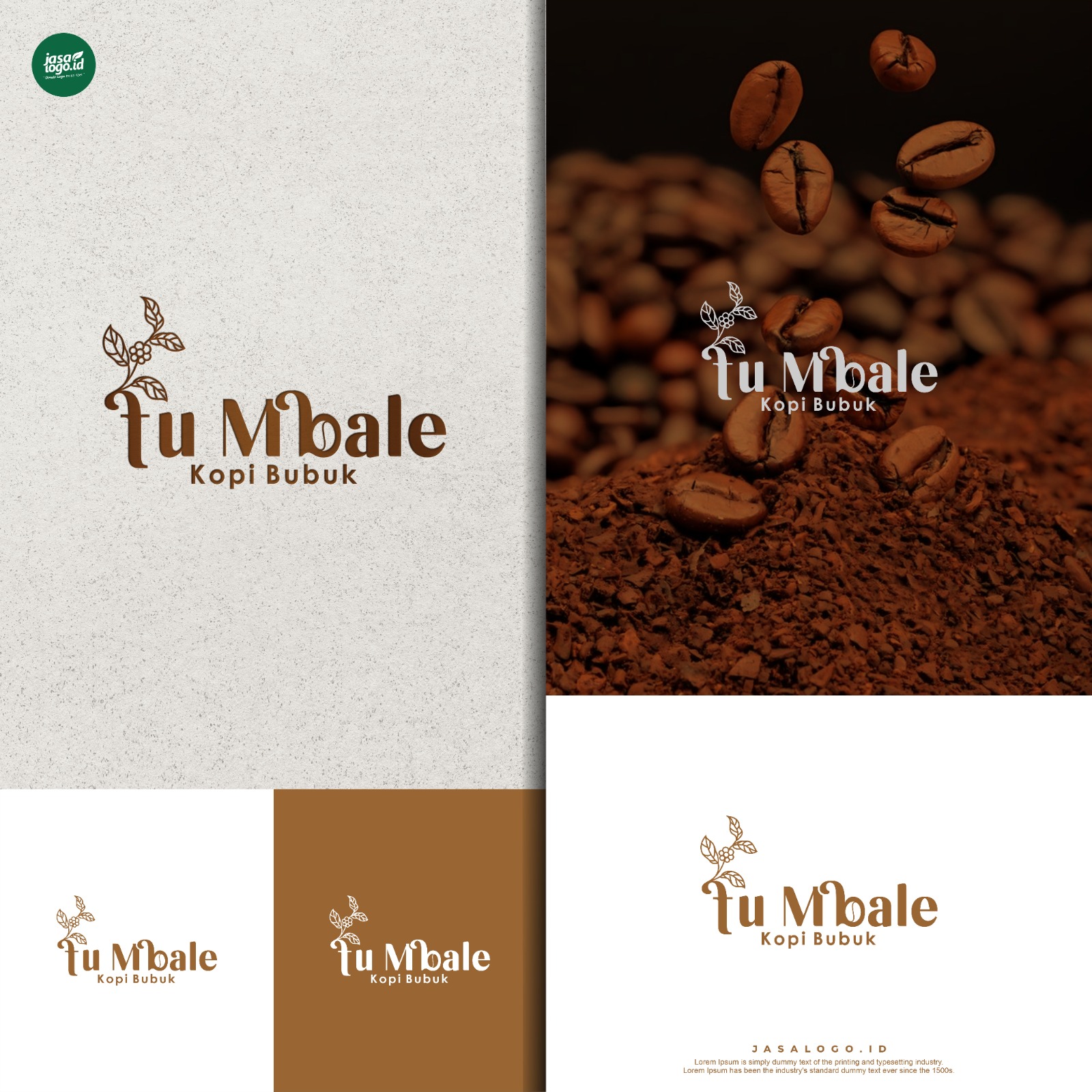
Desain logo coffee ini menggunakan gaya tipografi serif yang elegan sehingga menciptakan brand coffee yang elegan. Font serif elegan tersebut juga berguna memberi kesan brand coffee yang premium. Tipografi serif dalam logo tersebut memiliki gaya huruf sederhana, halus, dan memiliki sudut lancip.
Gaya tipografi pada logo coffee tersebut tidak hanya elegan tetapi juga tampil unik karena beberapa hurufnya memiliki ujung yang melengkung. Desain logo hanya memiliki tipografi dengan dekorasi daun yang sederhana. Kombinasi tipografi elegan dan simbol daun kecil menciptakan desain logo coffee yang elegan dan estetik.
Logo Warkop Logo
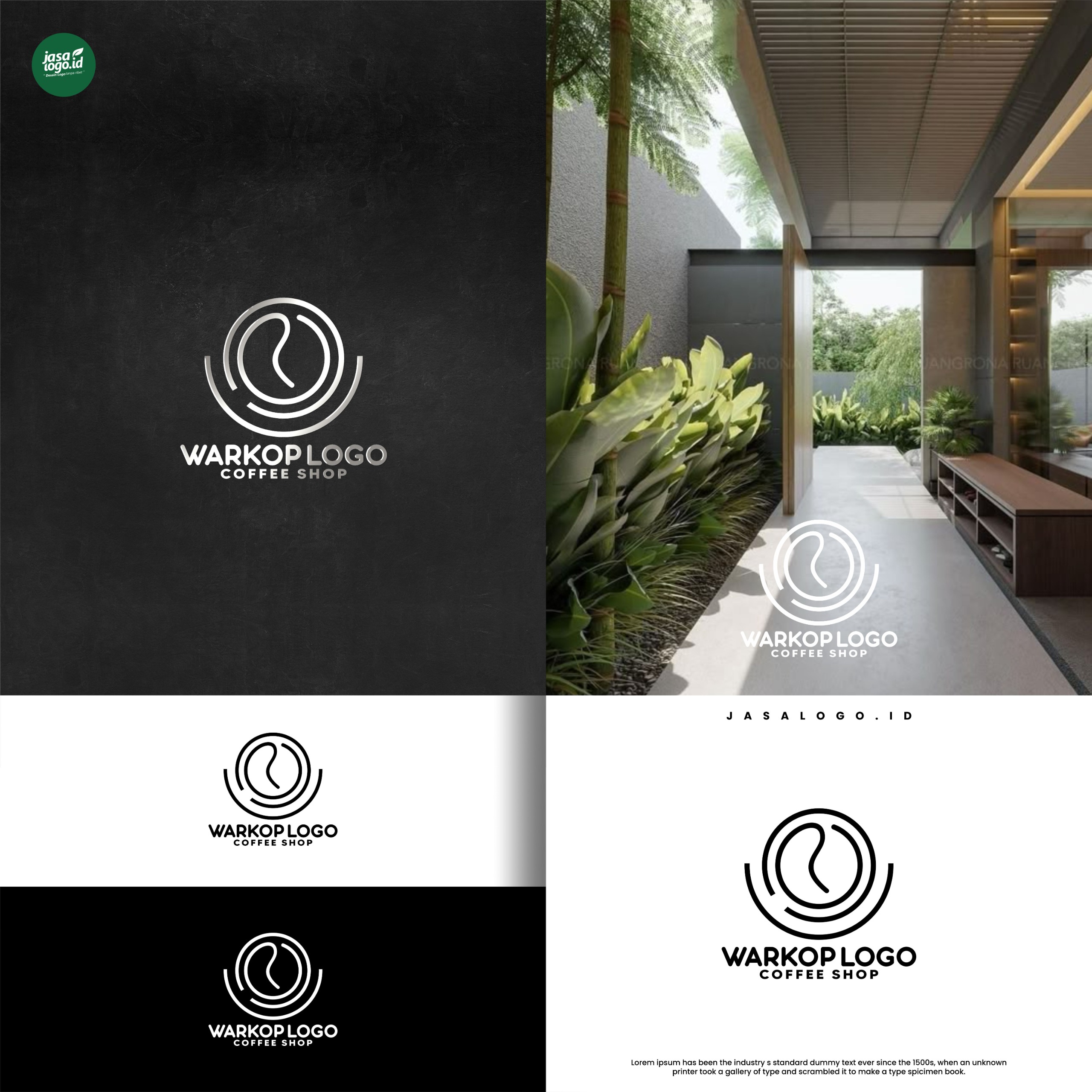
Style garis line art yang menciptakan bentuk lingkaran biji kopi tampil minimalis dan sederhana. Desain logo kopi line art ini menggunakan garis tipis yang elegan dan bersih. Style ikon geometris tersebut cocok dikombinasikan dengan gaya tipografi geometris yang sederhana.
Font sans serif yang digunakan memiliki gaya huruf geometris yang bersih dan menciptakan logo minimalis. Style font dalam brand coffee tersebut menciptakan tampilan minimalis dan estetik. Gaya huruf tersebut akan memberi kesan brand coffee modern yang premium dan profesional.
Logo Coffebee
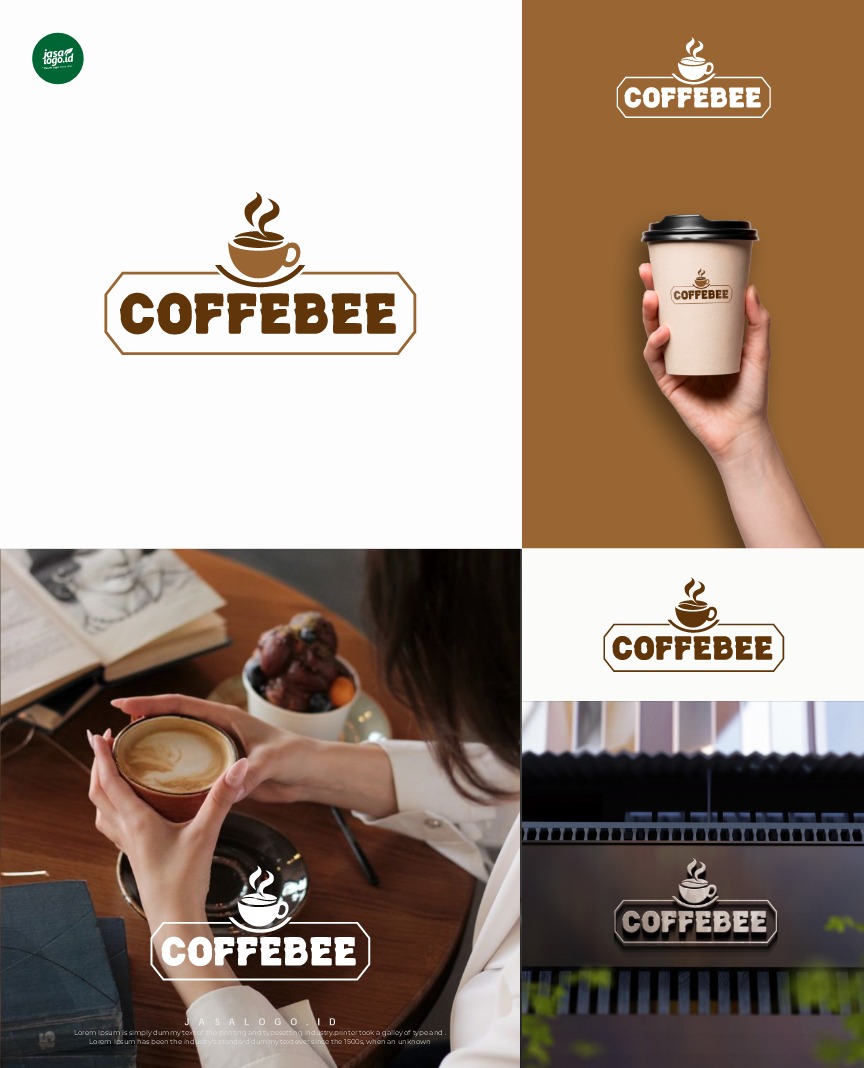
Desain brand coffebee memang banyak yang menggunakan font tipis yang elegan tetapi juga menggunakan font tebal. Gaya tipografi tersebut memiliki gaya huruf display yang unik dan memiliki huruf tebal. Style font tersebut membuat brand coffee memiliki kesan klasik dan premium.
Tipografi pada logo tersebut dibuat lebih besar dari simbol cangkir sehingga memiliki font tebal. Gaya font tebal membuat nama brand coffee mudah menarik perhatian dan dibaca oleh konsumen. Penggunaan gaya tipografi yang bergaya unik tersebut menciptakan kesan brand coffee yang premium.
Style font yang digunakan dalam logo kopi memiliki banyak variasi gaya yang menciptakan berbagai karakter brand. Font logo coffee sering menggunakan gaya huruf serif, script, dan sans serif yang memiliki gaya huruf elegan. Tipografi tersebut dalam logo coffee akan memberi kesan brand coffee yang estetik, premium, dan elegan.